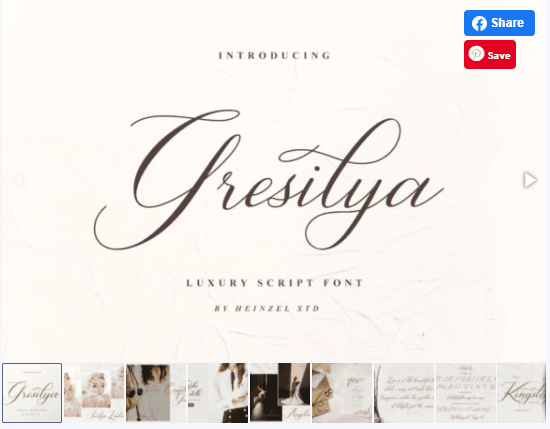
Gresilya Font
Gresilya - красивый и изысканный рукописный шрифт. Он имеет стильный, элегантный и современный вид, который можно использовать для логотипов, брендинга, приглашений, канцелярских товаров, свадебного дизайна, сообщений в социальных сетях и многого другого!